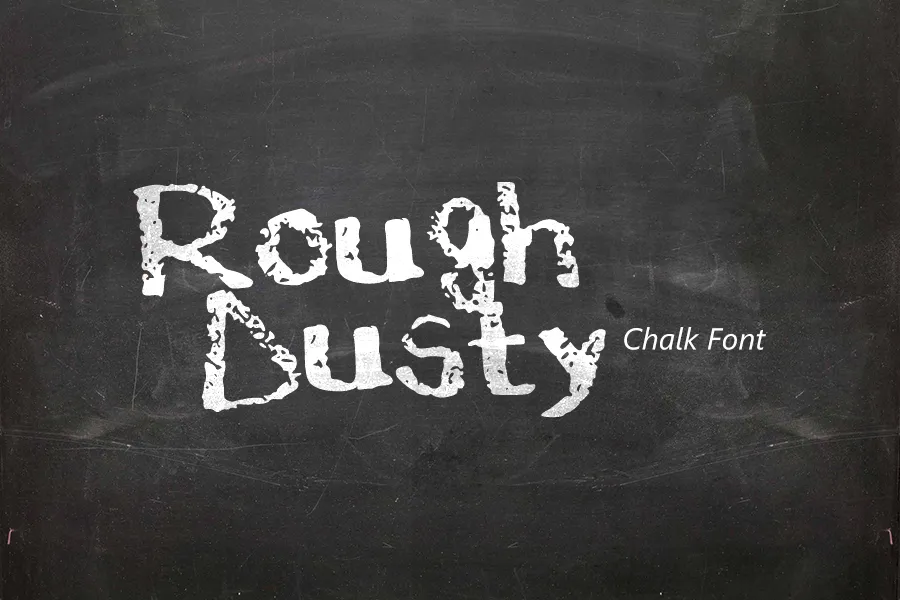
Esta fonte brush é perfeita para quem busca uma textura única e natural, criada por Hamilton com mão cheia. Com letras maiúsculas e minúsculas, números, caracteres especiais e algumas símbolos, ela oferece um grande leque de possibilidades. O melhor é que foi construída com um fluxo imperfeito, que irá dar ao seu texto uma aparência única e realista. Seja para criações artísticas ou gráficos semelhantes à arte livre, esta fonte Brush oferece um estilo elegante e orgânico, ideal para incorporar em designs digitais, como anúncios, logotipos e texturas de escrita. Para quem busca uma fonte que combine a simplicidade da tipografia com o encanto natural, Rough & Dusty Font é uma ótima escolha. Com sua mão cheia e suas nuances imperfeitas, essa fonte Brush oferece um tom elegante e orgânico, ideal para personalizar seu design de forma única. Perfect para qualquer tipo de aplicação gráfica, seja em criações digitais ou trabalhos manuais, esta fonte é uma pedida certa para os amantes da arte digital e do estilo único.